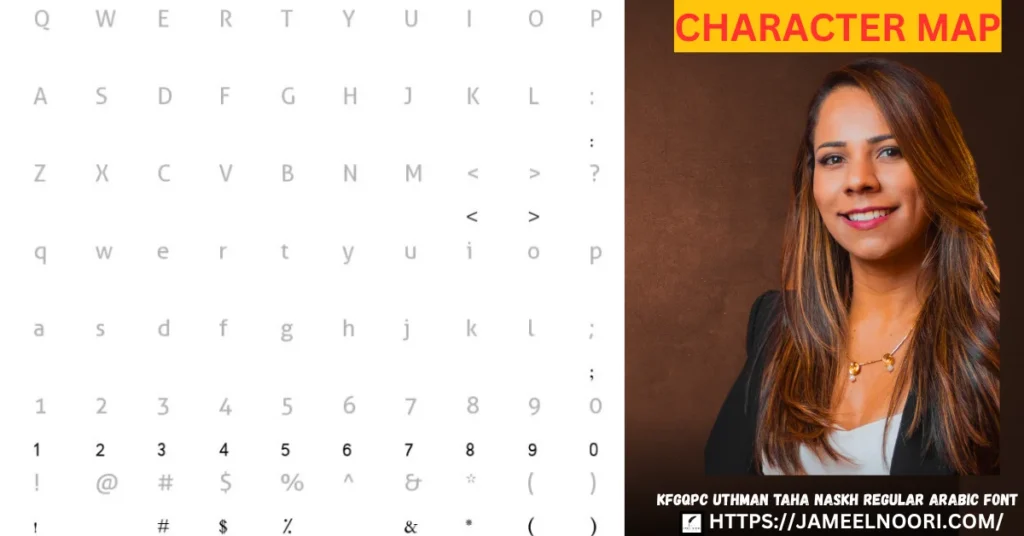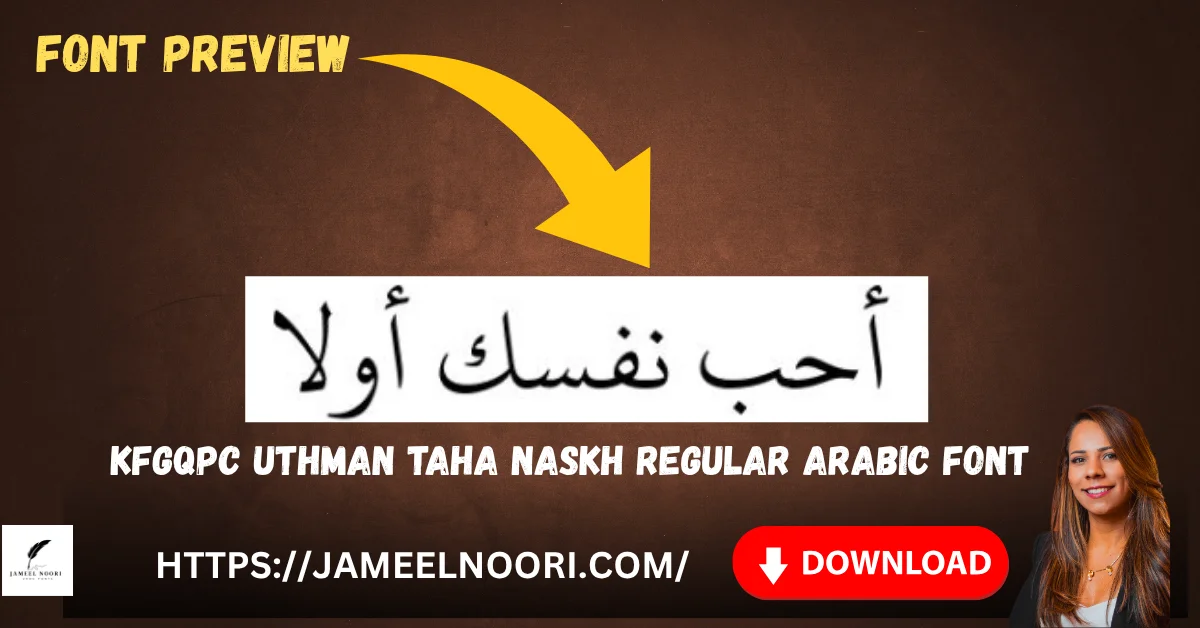
Introduction to KFGQPC Uthman Taha Naskh Regular Arabic Font
Pakistan mein khas tor par Lahore, Karachi aur Islamabad ke designers is font ko use karte hain presentations, magazines, aur web design ke liye. agar aap urdu fonts ya arabic fonts ki talash mein hain to yeh font aap ke liye best choice hai.
What is KFGQPC Uthman Taha Naskh Regular Arabic Font?
KFGQPC Uthman Taha Naskh Regular Arabic Font ek modern aur elegant Arabic font hai jo Naskh calligraphy style mein design kiya gaya hai. Ye font Arabic, Urdu, Punjabi aur Perso-Arabic scripts ke liye compatible hai.
Designers, magazines, bloggers aur presentations me iska extensive use hota hai kyunki ye readability aur aesthetic balance dono provide karta hai.
Key Features:
- Elegant Naskh style calligraphy – professional and clean look
- Works for Arabic, Urdu, and other regional scripts – versatile
Where to Use KFGQPC Uthman Taha Naskh Regular Arabic Font
KFGQPC Uthman Taha Naskh Regular Arabic Font ko aap kai jagah use kar sakte hain:
- PowerPoint Presentations – professional slides for business and education
- Web Design – Urdu websites, blogs, news portals
- Magazines and Newspapers – print media, professional publishing
- CorelDRAW – logo design, branding, flyers
- InPage Software – Urdu publishing, newspapers
Yes, it works well for web design and online content.